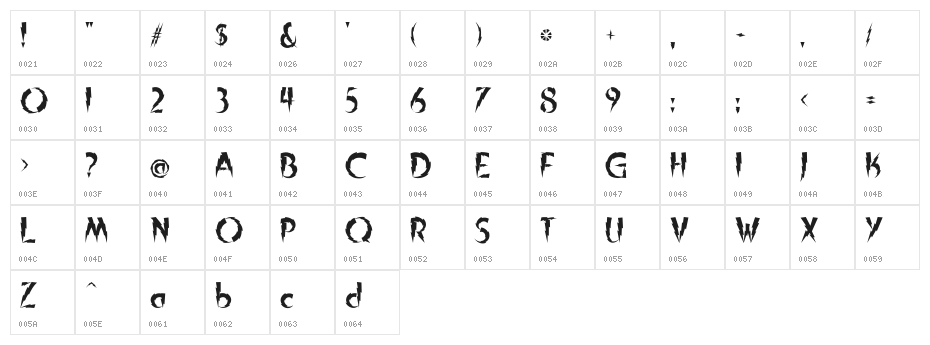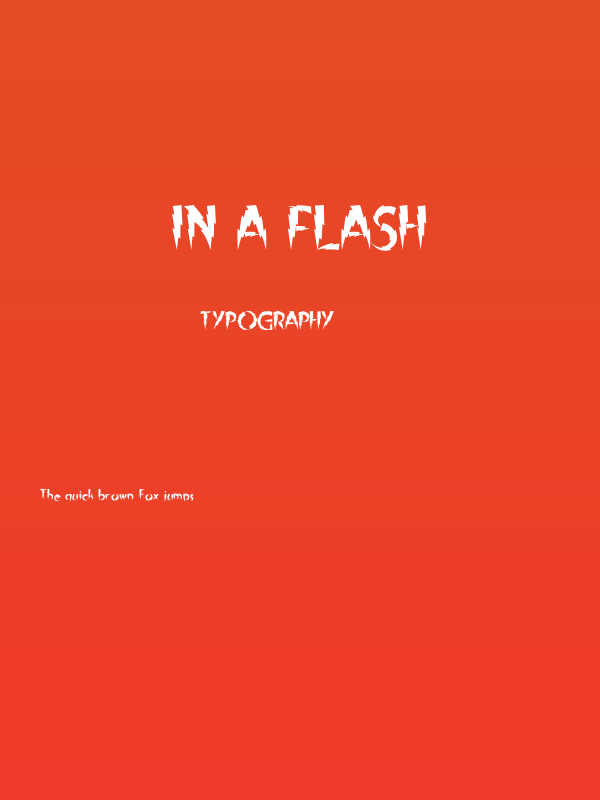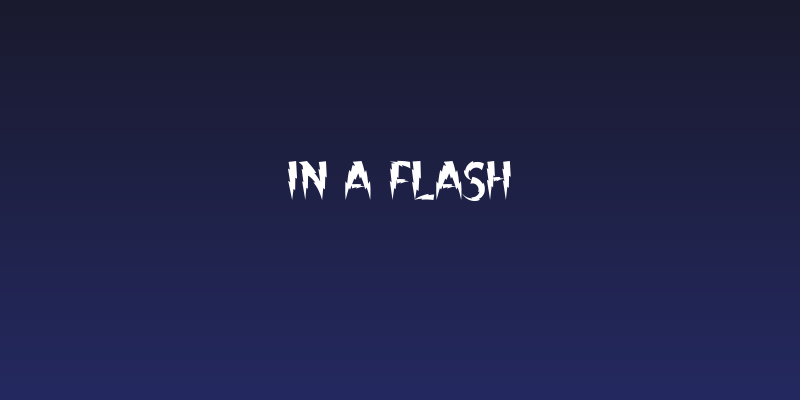
In A Flash Font
| 推荐项目 | Ideal for Halloween-themed designs, edgy posters, music album covers, or any project needing a dramatic and eye-catching font. |